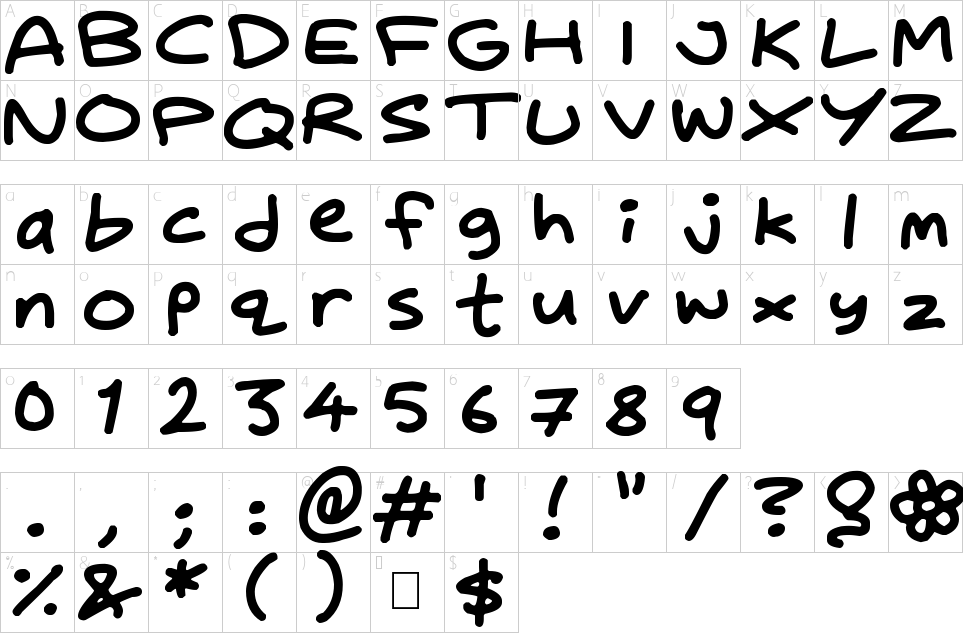
Daydreamer Font – Fonte Grátis
Daydreamer Font
A fonte ‘Daydreamer’ é uma escolha ideal para quem busca expressar sua personalidade criativa e sonhadora em seus projetos digitais. Desenvolvida pelo designer Darrell Flood, essa fonte foi projetada para trazer um toque de magia aos textos, sejam eles em aplicativos para Windows ou Mac. Com o seu design cuidadosamente elaborado, a ‘Daydreamer’ enriquece sua interface com uma elegância sofisticada e uma leveza que é capaz de capturar a essência do pensamento lúcido. Se você procura um recurso gráfico simples e inspirador para seus projetos, a fonte ‘Daydreamer’ pode ser uma ótima escolha. Seu design fluido e colorido se adapta perfeitamente para criações que exigem uma paleta de cores vibrante e texturas distintas. Com apenas um clique, você pode transformar suas ideias em algo mais rica e detalhado, tornando a ‘Daydreamer’ uma fonte indispensável para qualquer designer ou criativo digital.
Mapa de caracteres da fonte Daydreamer Font